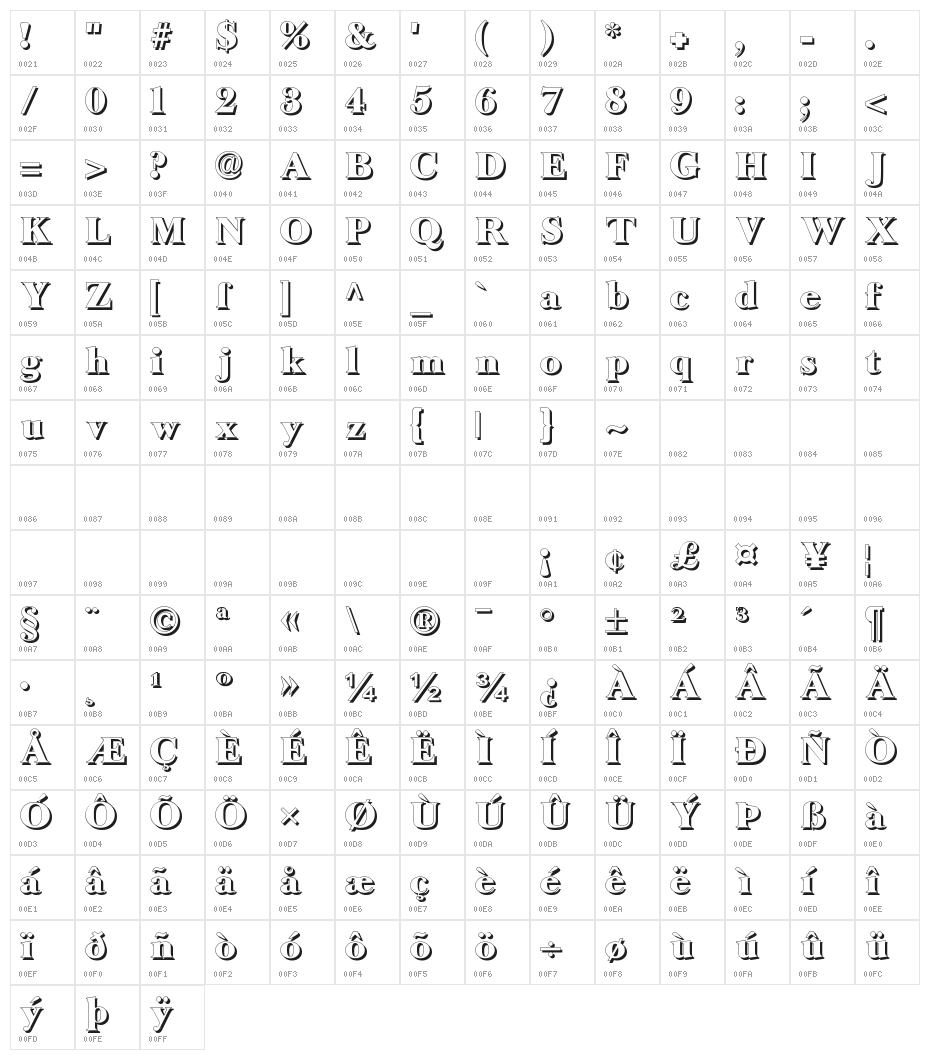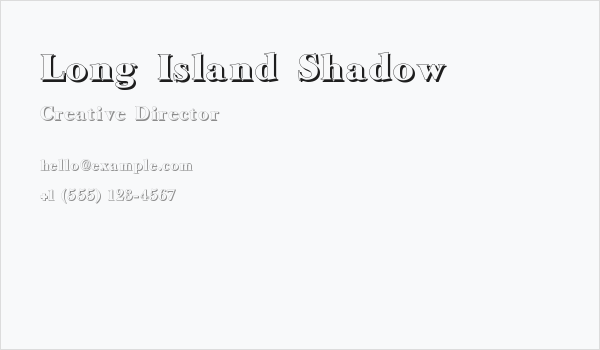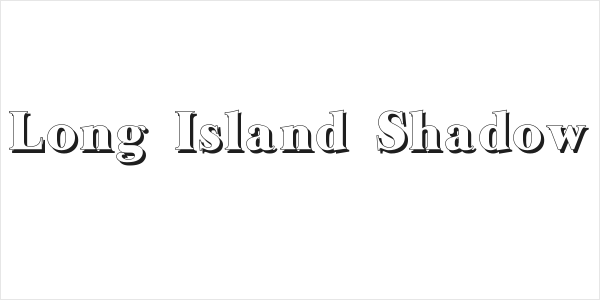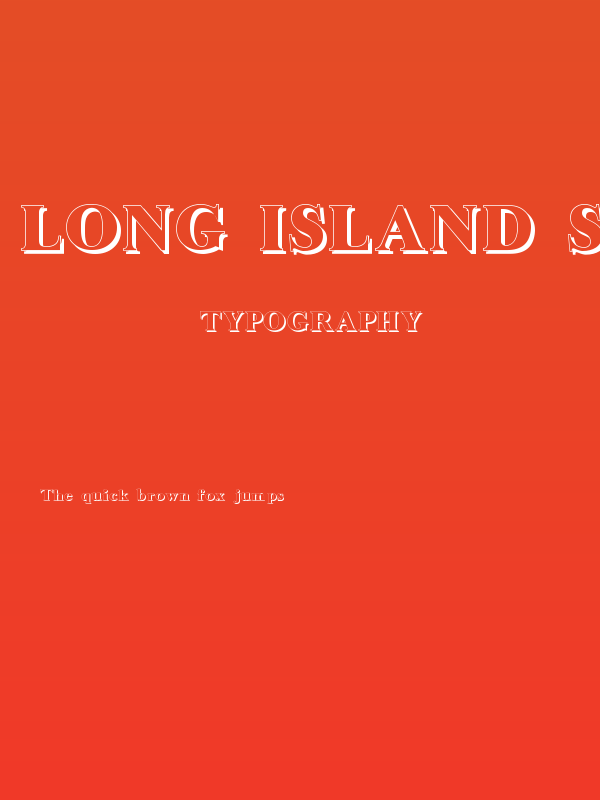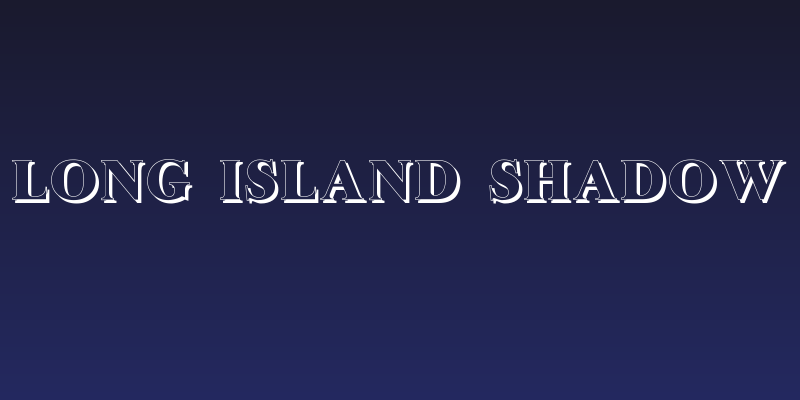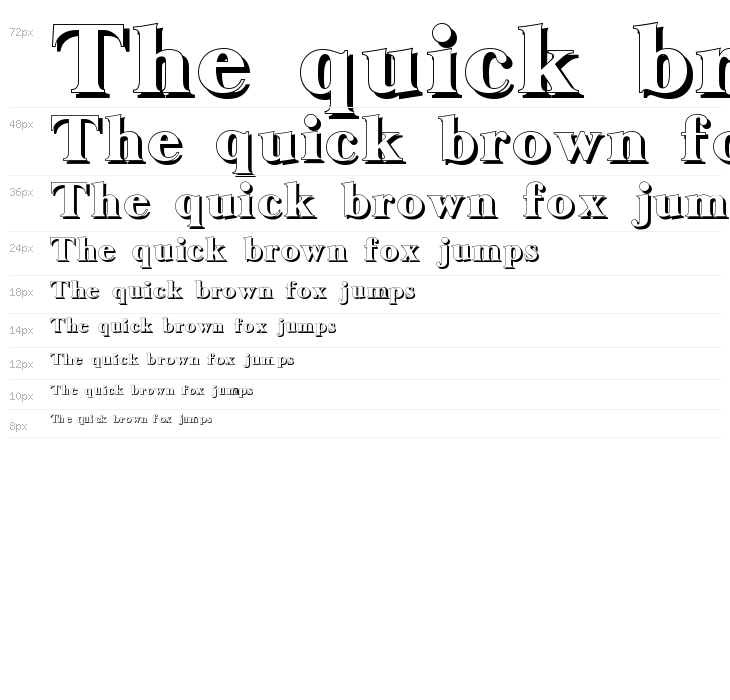
Long Island Shadow Font
| Progetti proposti | This font is perfect for projects that require a bold statement, such as posters, book covers, branding materials, and event invitations. |